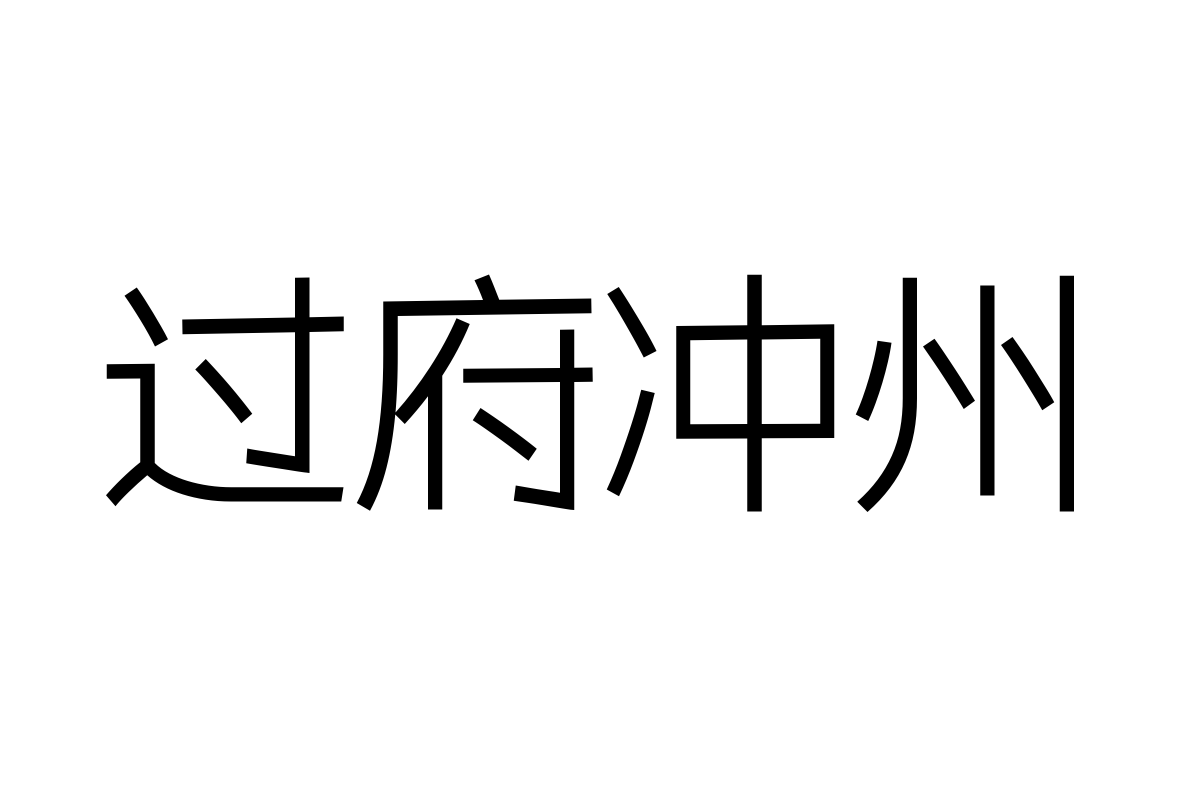
汉仪元隆黑-45是一款具有现代感的字体,适用于各种需要清晰、易读的文字设计。这款字体的特点是笔画流畅,字形规整,线条粗细适中,给人一种简洁明了的感觉。同时,其字体风格独特,具有较强的视觉冲击力,能够吸引人们的注意力。
在使用时,可以选择将其应用于标题、正文、广告等需要突出文字效果的场合。无论是在网页设计、海报制作还是书籍排版中,汉仪元隆黑-45都能够满足设计师的需求,创造出富有创意和美感的作品。